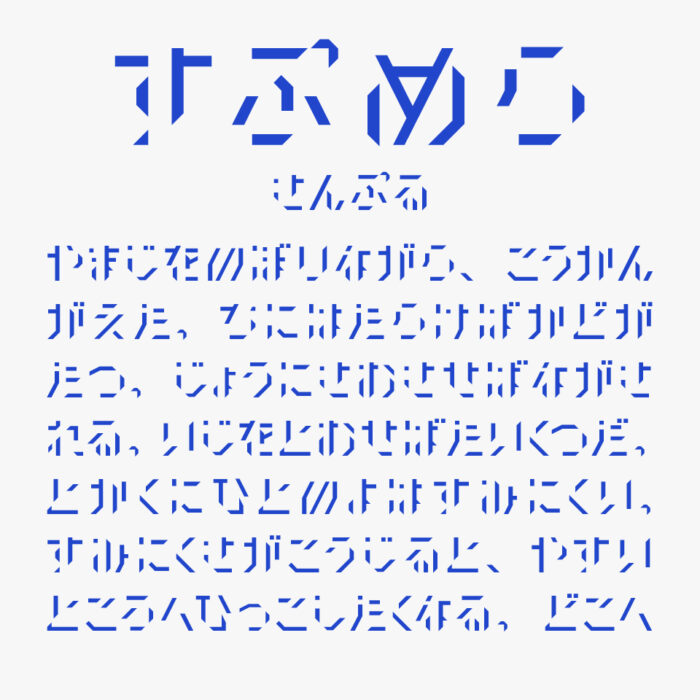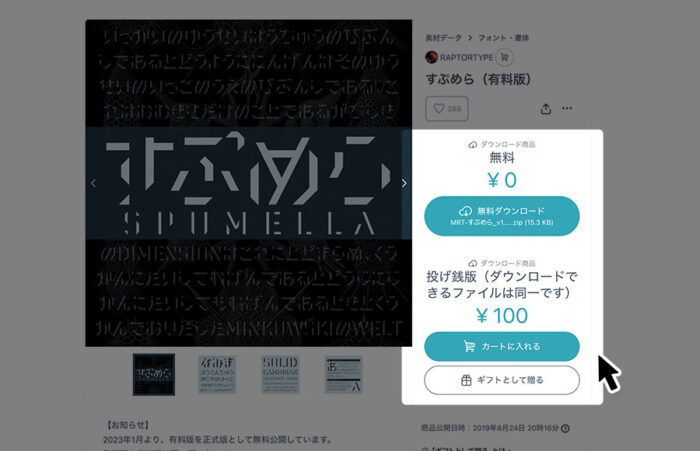
すぷめらフォントは、文字の一部を大胆に省略・分割したデザインフォントです。
直線的で幾何学的なパーツの組み合わせで作られているので、無機質な面白さのあり、機械ぽさやSFちっくな近未来感を感じるデザインフォントとなっています。
大胆な切り込みによって可読性は落ちてしまいますが、ビジュアルのインパクトを重視されているので、見出しやアクセントなどにぴったりなフォントです。
収録文字は、ひらがな・大文字アルファベット・一部記号が収録されています。